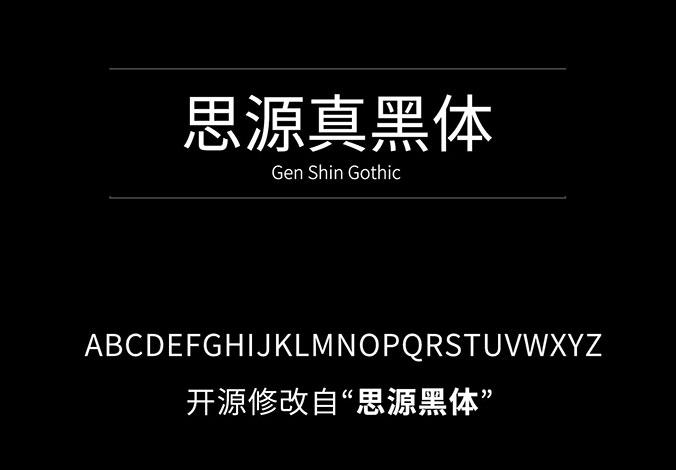
思源真黑体
细节更加锐利清晰,适用于大量文字阅读显示
思源真黑体(源真ゴシック)是基于开源字体“思源黑体”修改衍生而来,支持简体中文、繁体中文以及日文三种语言,保留了思源黑体原版的优雅以及高可读性的特色,也是提供了 7 种不同的字重、3种字形样式 (包括等宽字体、比例字体)。格式上转换成 TrueType (TTF) 版,细节上也做了很多的调整与变化,使得整套字体看起来更加锐利清晰,更适用于大量文字阅读显示、代码编程、排版、打印等。
思源真黑体的字重共有“一般、标准、中黑、细体、特细体、粗体、特黑体”7种。另外还有等宽字体 GenJyuuGothic - Monospace (适合用于编程写代码)、Proportional 比例字体 (字符宽度不同)。
细节上看起来更加锐利清晰,更适用于大量文字阅读显示、代码编程、排版、打印等。